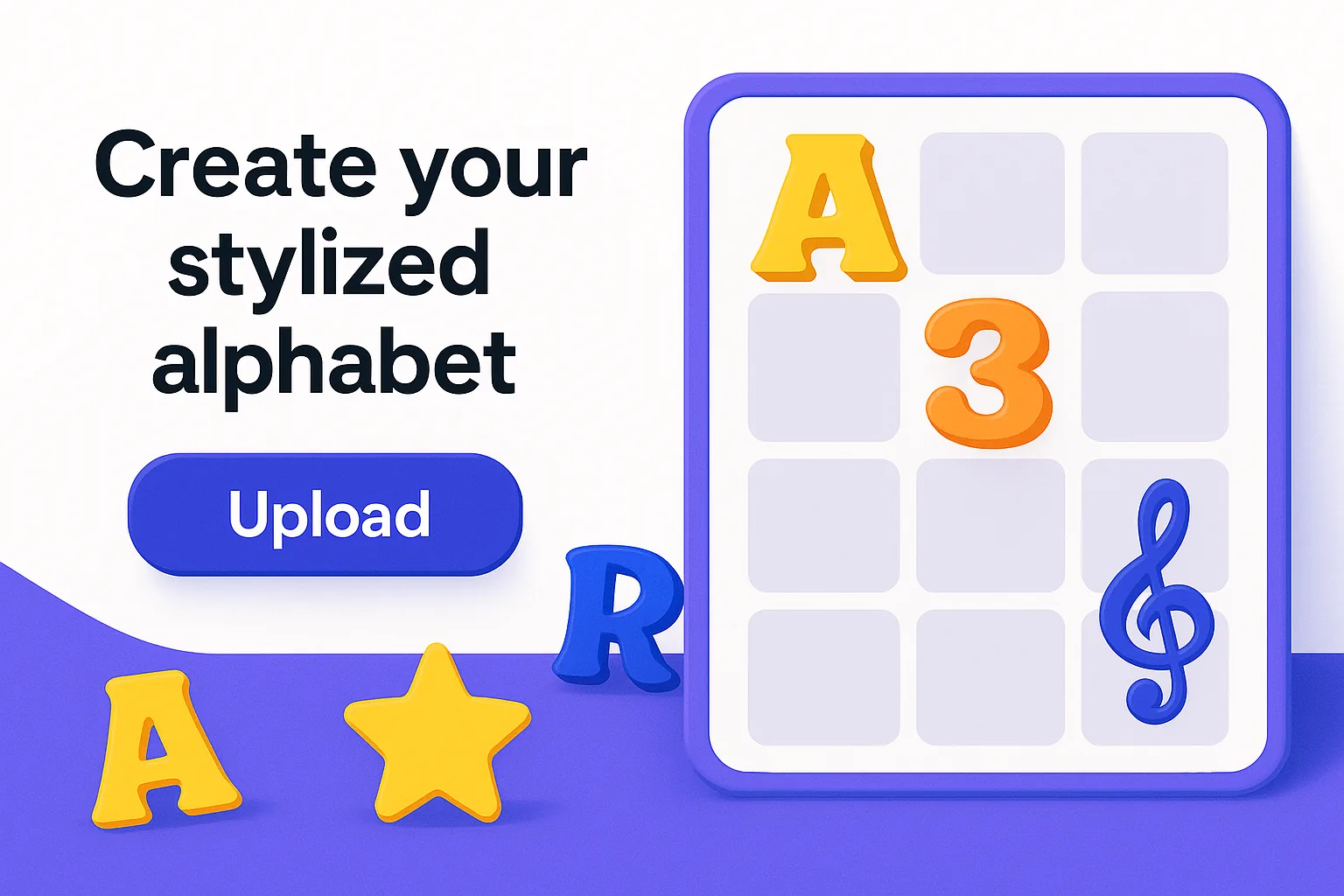
あなただけの手書き文字や独創的なレタリング、クリエイティブなデザインを、実際に使える本物のフォントに変えてみたいと思ったことはありませんか? デザイナーでもアーティストでも、あるいは字がきれいなだけの人でも、Alphabet Maker のおかげでオリジナルフォントの作成がかつてないほど簡単になりました。
この完全ガイドでは、あなたの作品を、ロゴやSNS、ゲーム、あらゆるクリエイティブプロジェクトで使えるプロ仕様のオリジナルフォントに変える方法を、具体的に解説します。
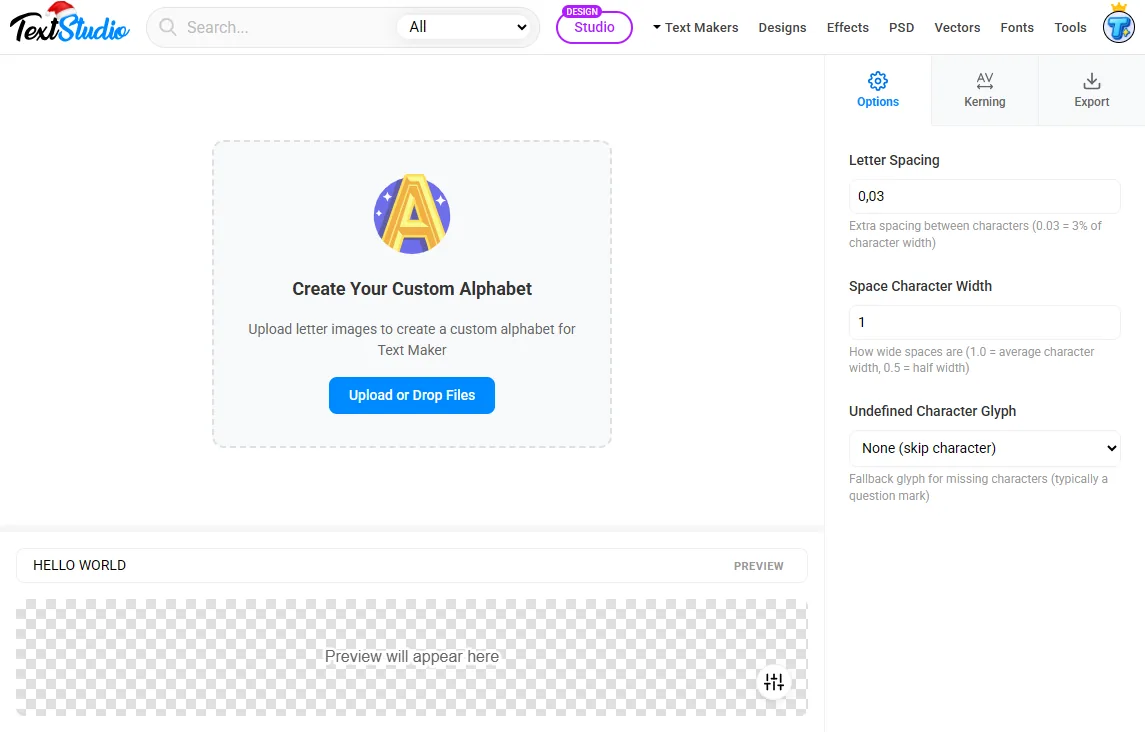
Alphabet Maker とは?
Alphabet Maker は、文字の画像をオリジナルフォントに変換できる無料のオンラインツールです。インストール不要で、ゼロからオンラインで自分だけのフォントを作成するいちばん手軽な方法のひとつです。専門知識や高額なサブスクリプションが必要な従来のフォント作成ソフトとは違い、Alphabet Maker は直感的なドラッグ&ドロップ操作で、ブラウザ上ですぐに使えます。
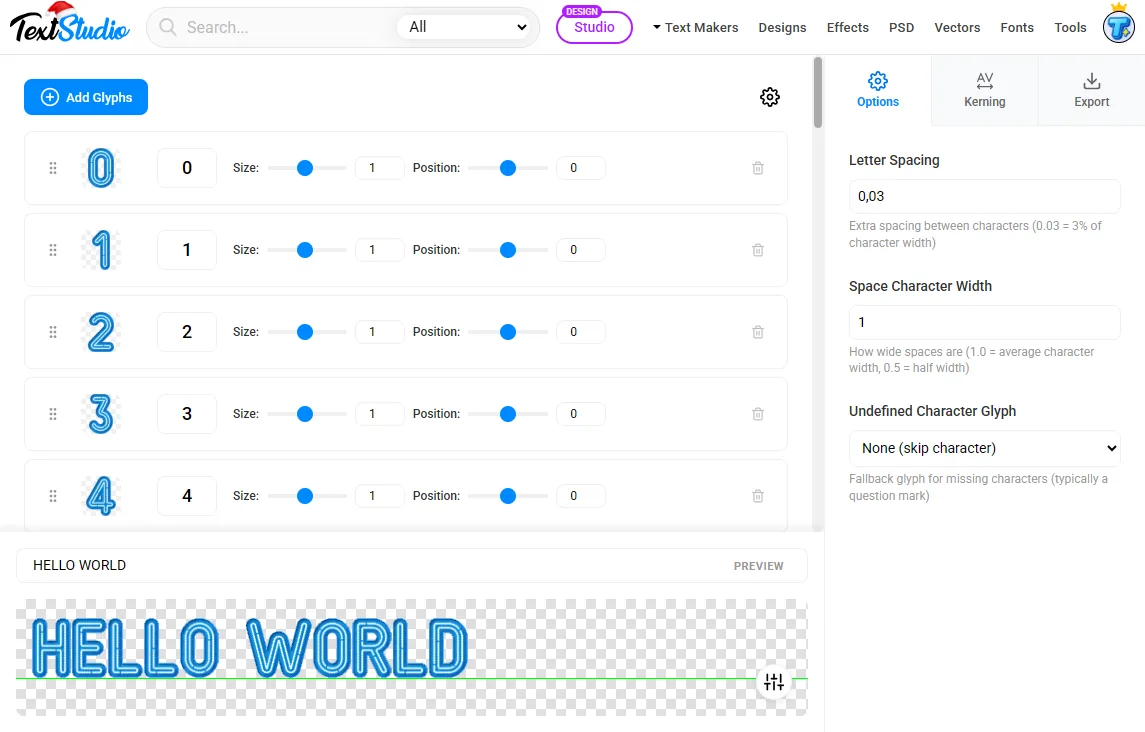
なぜオリジナルフォントを作るのか?
オリジナルのタイポグラフィは、あなたのブランドを際立たせます。何千人ものクリエイターが自分だけのフォントを作っている理由は、次のとおりです。
- 唯一無二のブランドアイデンティティ: 他の誰も持っていないタイポグラフィで差をつける
- 自由な表現: 通常のフォントエディタでは不可能な、テクスチャやグラデーション、エフェクトを使ったフォントをデザイン
- 個性を演出: 自分の手書き文字をデジタルフォント化して、結婚式の招待状や個人プロジェクトに
- 商用利用: オリジナルのフォントデザインを制作・販売して、不労所得を得る
- ゲーム開発: ゲームの世界観にぴったり合う、テーマ性のあるフォントをデザイン
ステップ別チュートリアル:はじめてのオリジナルフォント作成
🎨 ステップ1:文字を準備する
紙またはデジタルで文字を描いたりデザインしたりします。最良の結果を得るには、300 DPI でスキャンするか、背景を透明にした PNG ファイルとして書き出してください。
📤 ステップ2:Alphabet Maker にアップロード
Alphabet Maker にアクセスし、画像をアップロードエリアにドラッグします。複数のファイルを一度にアップロードすることも、文字一覧のシート全体をまとめてアップロードすることもできます。
🔤 ステップ3:文字を割り当てる
ビジュアルインターフェースを使って、それぞれの画像を対応する文字・数字・記号に割り当てます。ツールが文字シートから個々のグリフを自動的に検出します。
📏 ステップ4:字間を調整する
字間や行の高さ、個々の文字の位置を細かく調整します。リアルタイムプレビューを活用して、完璧なバランスと読みやすさを確認しましょう。
👁️ ステップ5:フォントをプレビューする
好きなテキストを入力して、フォントの仕上がりを確認します。よく使う単語やフレーズを試して、文字の組み合わせや全体の見え方をチェックしましょう。
💾 ステップ6:書き出して使う
フォントファイルをダウンロードし、Text Maker に読み込めば、背景やエフェクト、アニメーションを加えた魅力的なデザインを作成できます。
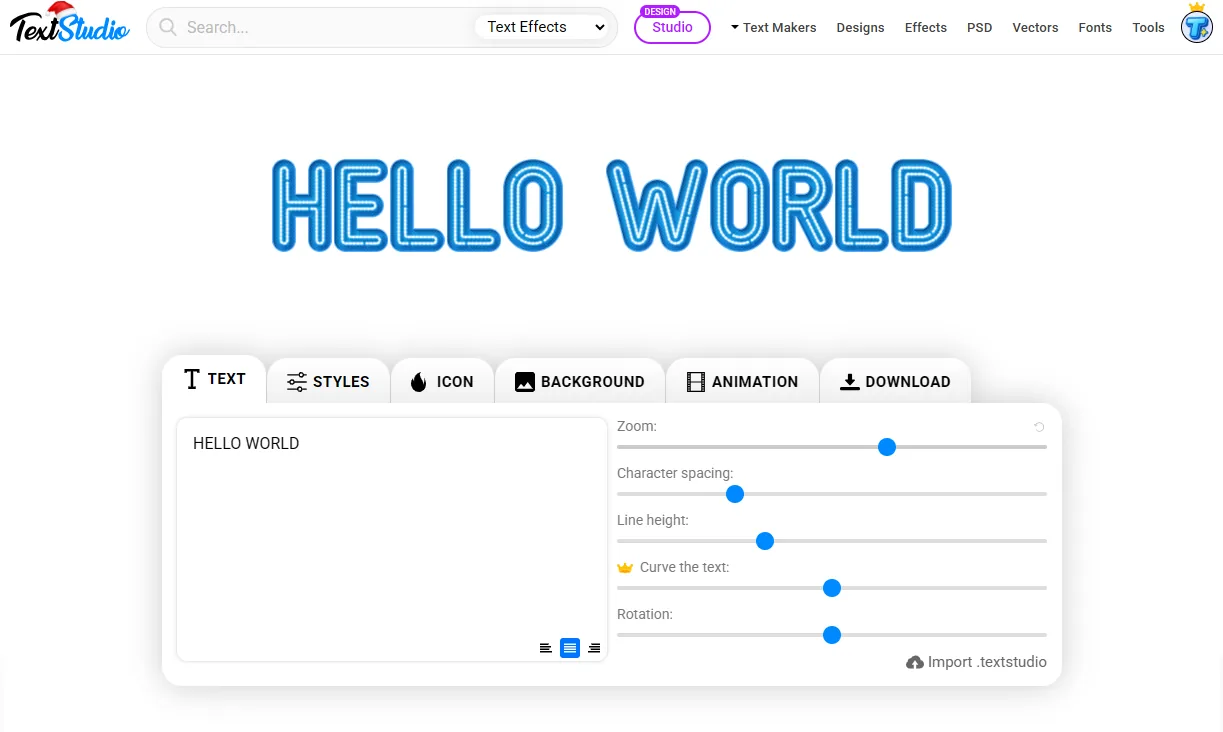
オリジナルフォントの活用アイデア
1. 手描きのアート系フォント
スケッチや絵画、デジタルイラストからフォントを作成しましょう。タイポグラフィを自分の作風に合わせたいアーティストに最適です。
2. テクスチャを活かしたタイポグラフィ
木材や石、布、金属などの素材を使って、質感のある文字を作りましょう。それらを撮影してオリジナルフォントに変換すれば、どんなデザインにも奥行きを加えられます。
3. 3Dレンダリングした文字
Blender などの3Dソフトで立体的な文字をデザインし、ライティングと影を付けてレンダリングします。それをフォントに変換すれば、立体感をそのまま保てます。
4. テーマ別フォントセット
特定のテーマに合わせたフォントを作成しましょう。
- 🎃 ハロウィンの不気味な文字
- 🎄 クリスマスの華やかなタイポグラフィ
- 🕹️ 80年代レトロなピクセルスタイル
- 🚀 未来的なSFフォント
5. 手書きサインフォント
自分の手書き文字をデジタル化して、次のような用途に活用できます。
- 温かみのある結婚式の招待状
- デジタル署名や書類
- パーソナルブランディングや名刺
- 手書き風のSNS投稿
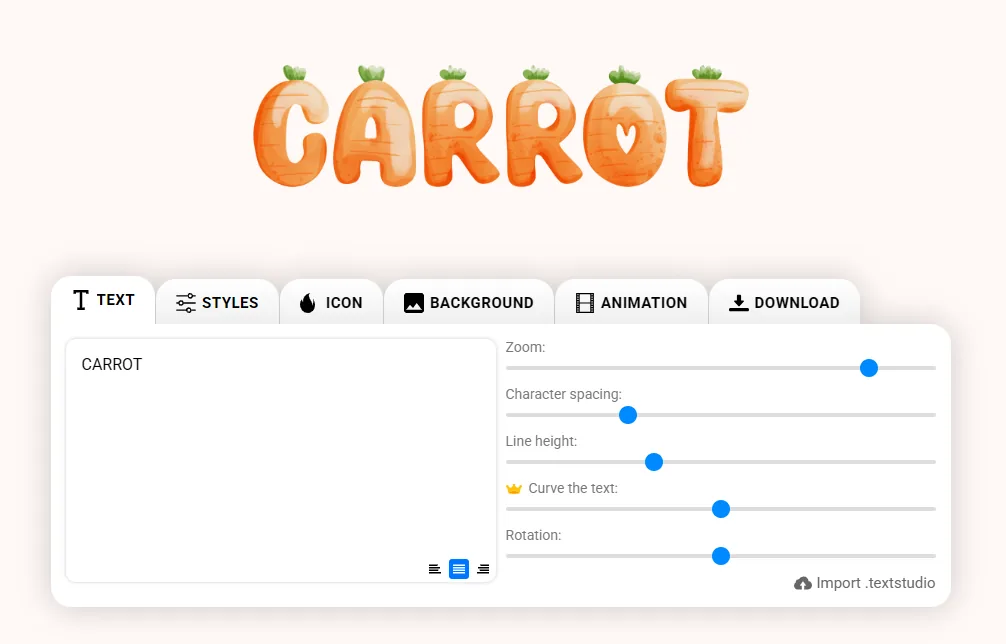
よりよいオリジナルフォントを作るためのプロのコツ
「プロ品質のオリジナルフォントを作る鍵は、一貫性です。文字の高さをそろえ、文字と文字の間隔に気を配りましょう。」
デザインのコツ
- ベースラインをそろえる: すべての文字が同じ仮想の線の上に乗るようにする
- 均一な太さ: すべての文字で線の太さを一定に保つ
- 明確なコントラスト: 文字と背景のコントラストを高くして、きれいに切り出せるようにする
- よく使う単語で確認: 「Hamburgevons」などの単語をプレビューして、すべての文字の組み合わせをチェックする
技術的なコツ
- 画像の品質: くっきりした仕上がりのために、最低でも300 DPIを使う
- ファイル形式: 背景が透明なPNGが最適
- 文字セット: 数字やよく使う句読点も忘れずに
- カーニングペア: AV、WA、To などの文字の組み合わせに特に注意する
実際の活用例
クリエイターたちがオリジナルフォントをどのように活用しているかをご紹介します。
ブランディングとマーケティング
企業は、ビジュアルアイデンティティの一部となる独自のフォントを作成しています。テックスタートアップから小さなブティックまで、オリジナルのタイポグラフィは、競争の激しい市場でブランドを際立たせるのに役立ちます。
SNSコンテンツ
Instagram のクリエイターや YouTuber、TikTok ユーザーは、オリジナルフォントを使ってコンテンツ全体で一貫した世界観を保ち、投稿がひと目でわかるようにしています。
ゲーム開発
インディーゲームの開発者は、ピクセルアート風のタイポグラフィから手描きのファンタジー文字まで、ゲームのアートスタイルにぴったり合うフォントを作成しています。
印刷デザイン
ウェディングプランナーやイベント主催者、印刷デザイナーは、オリジナルフォントを使って、他にはない招待状やポスター、宣伝物を制作しています。
Alphabet Maker と従来のフォント作成ツールの比較
複雑なフォント作成ソフトではなく、Alphabet Maker を選ぶ理由は何でしょうか。
| 特徴 | Alphabet Maker | 従来のツール |
|---|---|---|
| 習得のしやすさ | ✅ 不要 - すぐに始められる | ❌ 難しい - マスターに数週間 |
| 費用 | ✅ ずっと無料 | ❌ 200〜500ドル以上 |
| インストール | ✅ ブラウザで完結 | ❌ 大容量のダウンロードが必要 |
| 画像への対応 | ✅ アート作品に最適 | ❌ ベクター中心 |
| プレビュー | ✅ リアルタイム | ❌ 書き出さないと確認できない |
Text Maker との連携
オリジナルフォントを作成したら、本当の魔法は Text Maker で起こります。この連携ツールを使えば、次のことができます。
- 背景やグラデーションを適用し、影のエフェクトを追加する
- アニメーションやモーショングラフィックスを作成する
- 印刷やウェブ向けに高解像度の画像を書き出す
- プロジェクトやテンプレートを保存して、後で使う
Alphabet Maker は本当に無料ですか?
はい! Alphabet Maker は完全無料で、隠れた費用も、透かしも、制限もありません。1円もかけずに、無制限にフォントを作成できます。
どんな画像形式が使えますか?
Alphabet Maker は PNG、JPG、SVG、WebP をはじめ、一般的な画像形式のほとんどに対応しています。最良の結果を得るには、背景が透明な PNG を使ってください。
作ったフォントを商用利用できますか?
はい! あなたが作成したフォントはあなたのものなので、好きなように使えます。プレミアムサブスクリプションを利用すれば、商用プロジェクトや販売にも使用できます。多くのクリエイターはAIでフォントを販売して、安定した不労所得を得てさえいます。
デザインの経験は必要ですか?
まったく必要ありません! Alphabet Maker は誰でも使えるように設計されています。直感的なインターフェースが、各ステップをわかりやすく案内します。
作成したフォントは後から編集できますか?
はい、フォントのプロジェクトを保存して、いつでも戻って編集できます。保存したファイルを読み込めば、続きから作業できます。